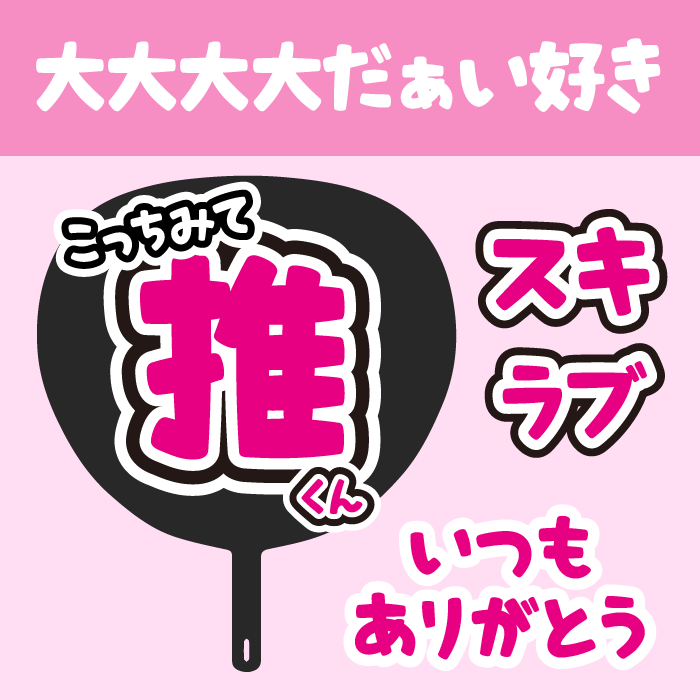
今回は、アイドルなどの応援グッズ「うちわ文字」におすすめのフリーフォントをまとめてみました。
アイドルや歌手のライブやコンサートに参戦する際に使える「応援うちわ」にぴったりなフォントをご紹介します。とっても可愛い文字ばかりなので、ライブでなどの目立つこと間違いなし!
「うちわ文字」におすすめフリーフォントのまとめ
「うちわ文字」以外でもTシャツやアクスタなどさまざまな推し活の応援グッズで利用できるフォントばかりです。
以下のサンプルは、本記事で紹介しているフォントの一部です!このような可愛くて「うちわ文字」にぴったりのフリーフォントをご紹介しているので、ぜひ参考にしてみてくださいね。
以下より「応援うちわ」におすすめのフォントを紹介します!
【定番】にくまる
にくまるフォントは、まるまるっとぷっくらしているフォルムは愛らしく可愛らしいデザインになっています。
推し活グッズを手作り人にとっても人気で「応援うちわ」で利用されている方が多いフォントの1つです。
【定番】ましゅまろポップ ハート
ましゅまろポップ ハートフォントは、ぷっくりしている文字の中にハートが散りばめられているかわいいフォントです。
ハートが入っていることで、アイドルやアーティスの「応援うちわ」にぴったりなフォントです。
推しゴフォントは、推しうちわ制作・推し活グッズ制作用として作られたフォントです!
そのため、やわらかく可愛らしい印象ですが、どっしりと目立つ太さもあるデザインです。うちわ制作でよく利用する指ハート・ハート・ダイヤモンド・キラキラなどのアイコンが35種類使うこともできるフォントです!
チェックポイント
チェックポイントフォントは、しっかりとした太さがありながら、丸みがあって可愛いフォントとなっているので、応援うちわ文字に人気あるフォントです。
漢字の収録数も多いので、推しの名前もきっと打てるはずです!
【定番】Cherry Bomb
Cherry Bomb One(チェリーボム)フォントは、プクプクとした丸っこいフォルムと、手書き感のある可愛らしい文字フォントです。かわいい応援うちわを作りたいときには、ぴったりのフォントです。
ななキュンのうた
ななキュンのうたフォントは、「音符」や「ハート」が隠れている可愛らしいデザインフォントです。
使用する文字によって雰囲気がガラッと変わるので、応援うちわを作るのが楽しみになりますね!
【定番】ふぁんしーはーと
ふぁんしーはーとフォントは、フチ文字になっており、文字の中にハートが隠れているキュートなフォントです。
推し活グッズ制作には定番で人気フォントの1つです。
【定番】みんとキッス
みんとキッスフォントは、切り込みと光沢が入っているフォントです
太さもあるので、コンサートホールなどの遠くからも読める文字となっているので、応援うちわぴったりなフォントの1つです。漢字が含まれていないフォントなので、ひらがな・カタカナに使いたい人におすすめです。
きょうりゅうグラタン
きょうりゅうグラタンは、とにかく太く、ユニークな形をしているので親しみのあるフォルム。最近人気が急上昇してきている可愛いらしいフォントです。
漢字の文字数が少なめなので、推し名前が含まれていない場合があります。
トガリテ
トガリテフォントは、トゲが生えているようなデザインが結構目立つフォント。
トゲトゲの装飾が、ゴスロリ系のカッコいい&可愛いフォントです。他の人と被りづらいフォントを探している方におすすめなフォントです。
どきどきファンタジア
どきどきファンタジアフォントは、太めの丸ゴシックに、ツヤ表現の装飾がついたユニークでデザインです。光沢感がとってもかわいです。大きめの文字に使うのがおすすめです!
【定番】けいふぉんと
けいフォントは、スタンダードなゴシック体タイプですが文字もちょうどよい太さで読みやすく、少し動きがあるので可愛らしい、そのため使いやすいフォントです。オタ活グッツやオタ活動画制作などさまざまなシーンおいて定番で、人気のあるフォントです。
【定番】ラノベPOP
ラノベPOPフォントは、けいふぉんとと同様に「オタ活・推し活」のグッツ制作では定番フォントの1つです。
マジックペンで書いたような手書き感ある文字となっている、ちょっと楽しい「応援うちわ」を作るにはぴったりなフォントです。
くらむぼん
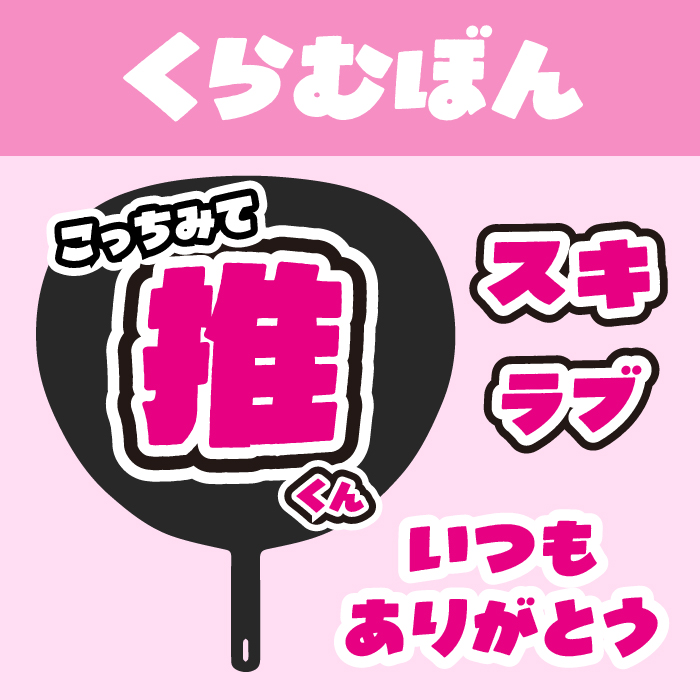
くらむぼんフォントは、ボンッと動きがあるとても可愛らしい極太フォントです。太さもあるので、インパクトや目立つフォントとなっているので、応援うちわに最適なフォントです。
源暎きわみゴ
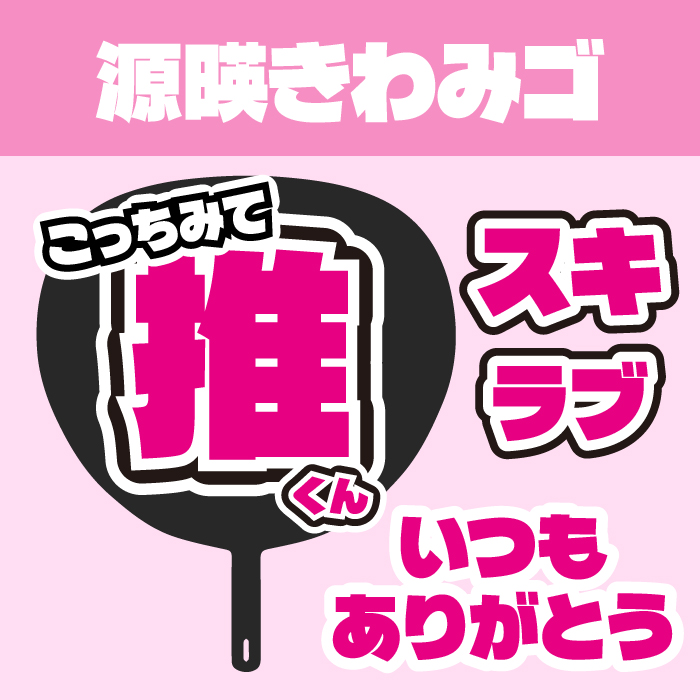
源暎きわみゴは、インパクトのある超極太ゴシックです。インパクトはあるけど視認性や判読性も高く応援うちわや推し活グッツ制作などにぴったりなフォントです。
ビルと谷間と高架下
ビルの谷間と高架下フォントは、漢字とひらがな、カタカナのでこぼこ感が可愛いらしいデザインフォントです。デコボコしている印象がとっても愛らしいので、かわいい応援うちわを作るならこちらのフォントもおすすめです。
【定番】コーポレート・ロゴ(ラウンド)
コーポレート・ロゴ丸フォントは、太さがあり、インパクトもあるので応援うちわに最適な丸ゴシックフォントです。
可愛くなりすぎずに固くなりすぎずなバランスの良いフォントです。
Mike(づにのい)
Mike(づにのい)フォントは、極太な角丸と線が特徴的なぷくっとした可愛い文字です。推し活文字としてとても人気あるフォントです。
ほのぼのポップ
ほのぼのポップォントは、文字の輪郭が線になっているデザインフォントです。文字もほのぼのとした手書き感がラフな雰囲気があり可愛らしいフォントです。
プイッコ
プイッコフォントは、マジックで書いたような極太で、線幅がランダムになっている遊びココロが満載なデザインになっています。
だるまドロップ
だるまドロップフォントは、にじんでいるような質感が少し暖かい印象を作り出すフォントです。応援したい熱い気持ちや柔らか印象を作り出すにはぴったりなフォントです。
キルゴUフォントは、太さが極太で、ゴツゴツとしたインパクトもあるので、応援うちわに最適にぴったりなフォントです。文字数が多い漢字などの場合は、少し潰れた印象がでてしまう可能性があるので、ひらがな・カナカナを使ってみるのがおすすめです。